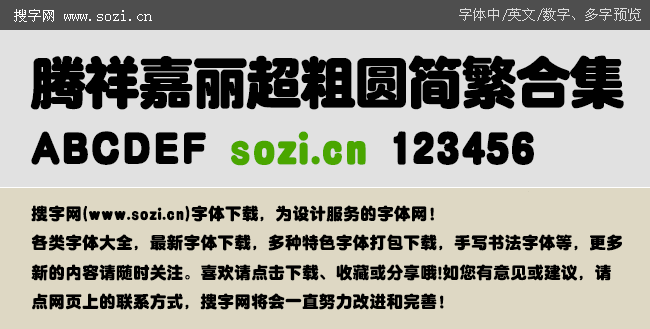
騰祥嘉麗超粗圓簡(jiǎn)繁合集
搜字網(wǎng)提供一款騰祥嘉麗超粗圓簡(jiǎn)繁合集中文藝術(shù)字體下載,騰祥嘉麗超粗圓是一款應(yīng)用于設(shè)計(jì)方面的簡(jiǎn)體中文漢字,該字體線條粗壯有力,字形大方得體,整體效果出眾,并且字庫(kù)完整,可用于藝術(shù)設(shè)計(jì)、包裝印刷、簽名設(shè)計(jì)、圖形設(shè)計(jì)等領(lǐng)域。